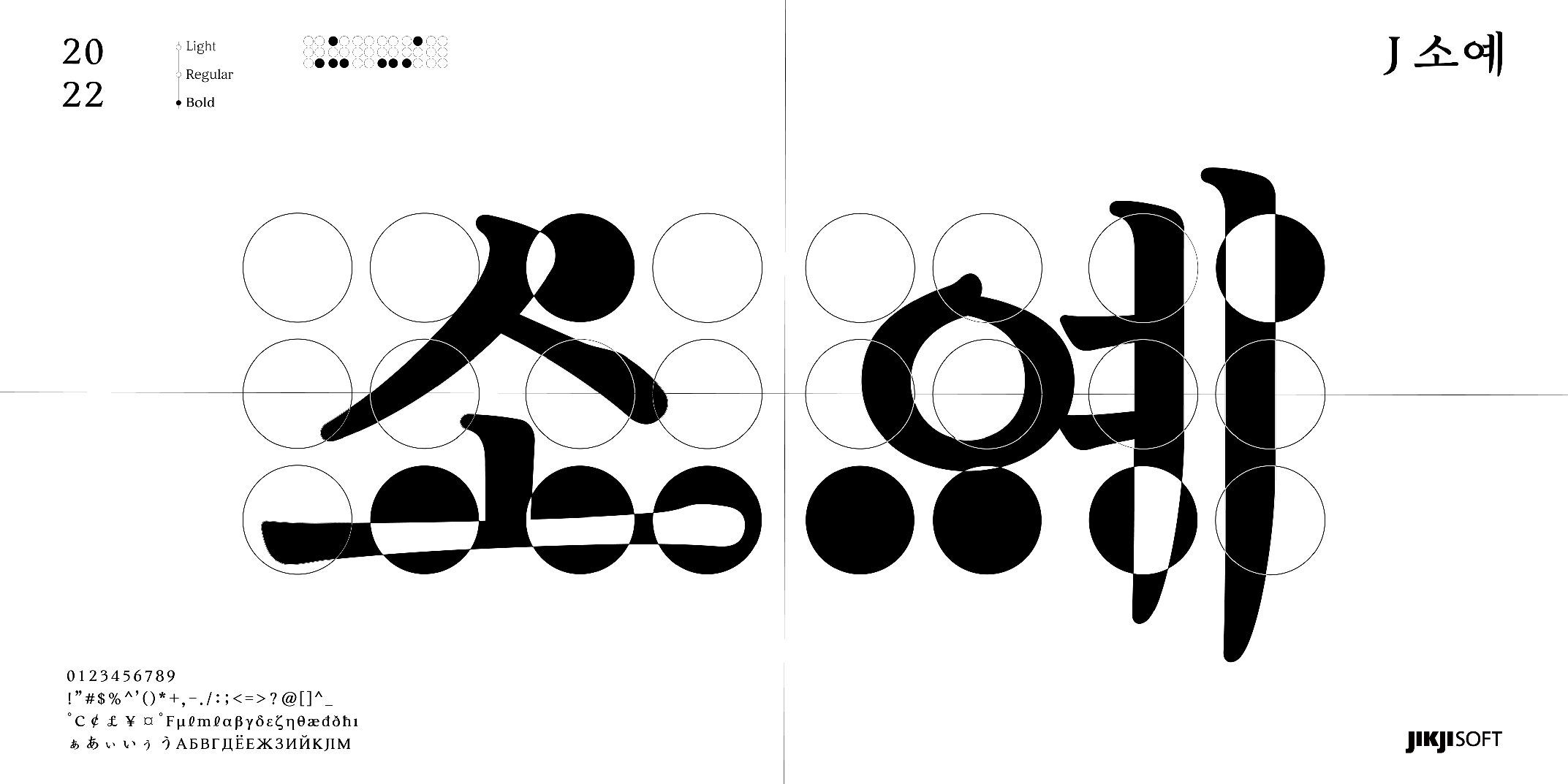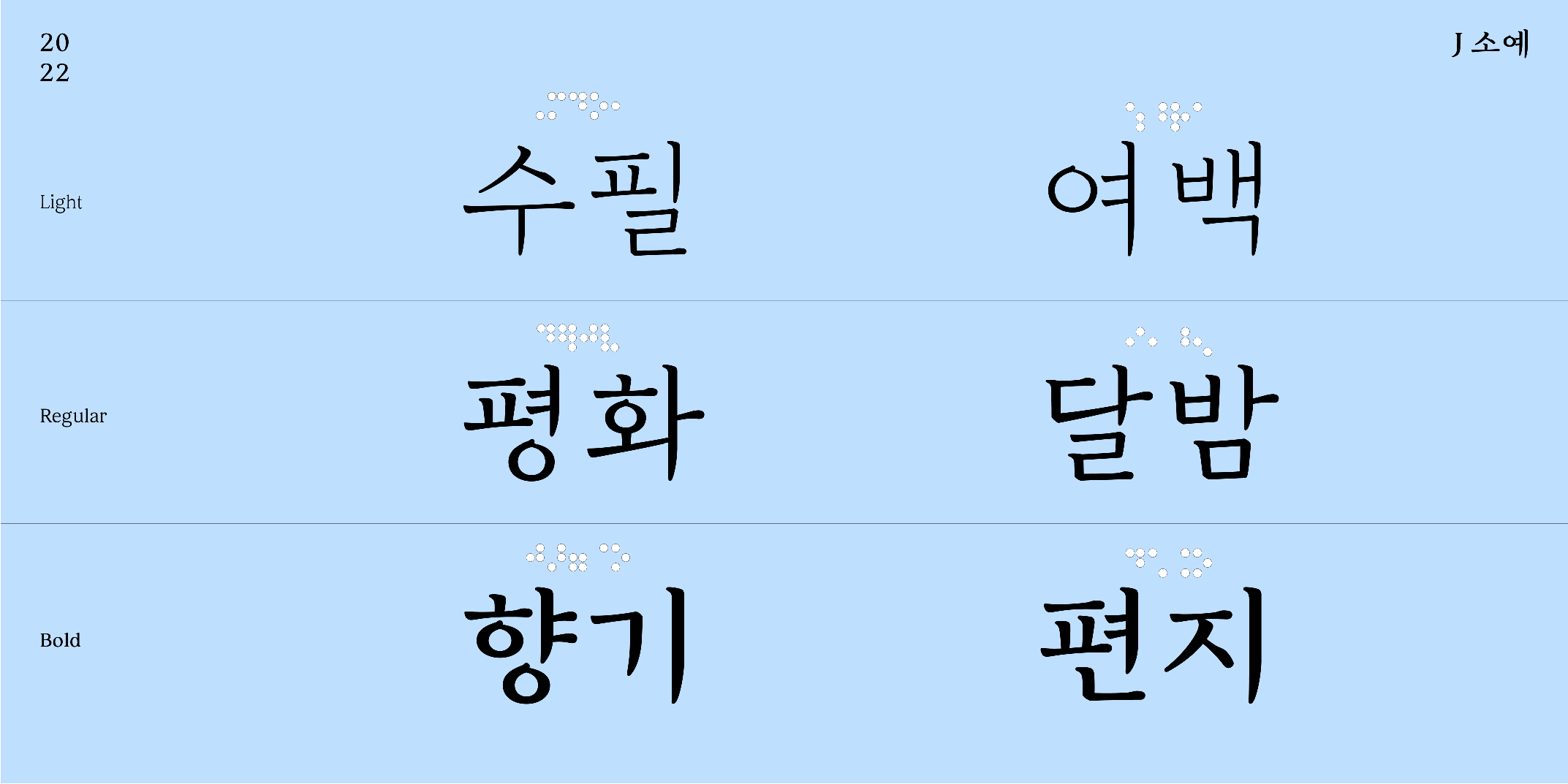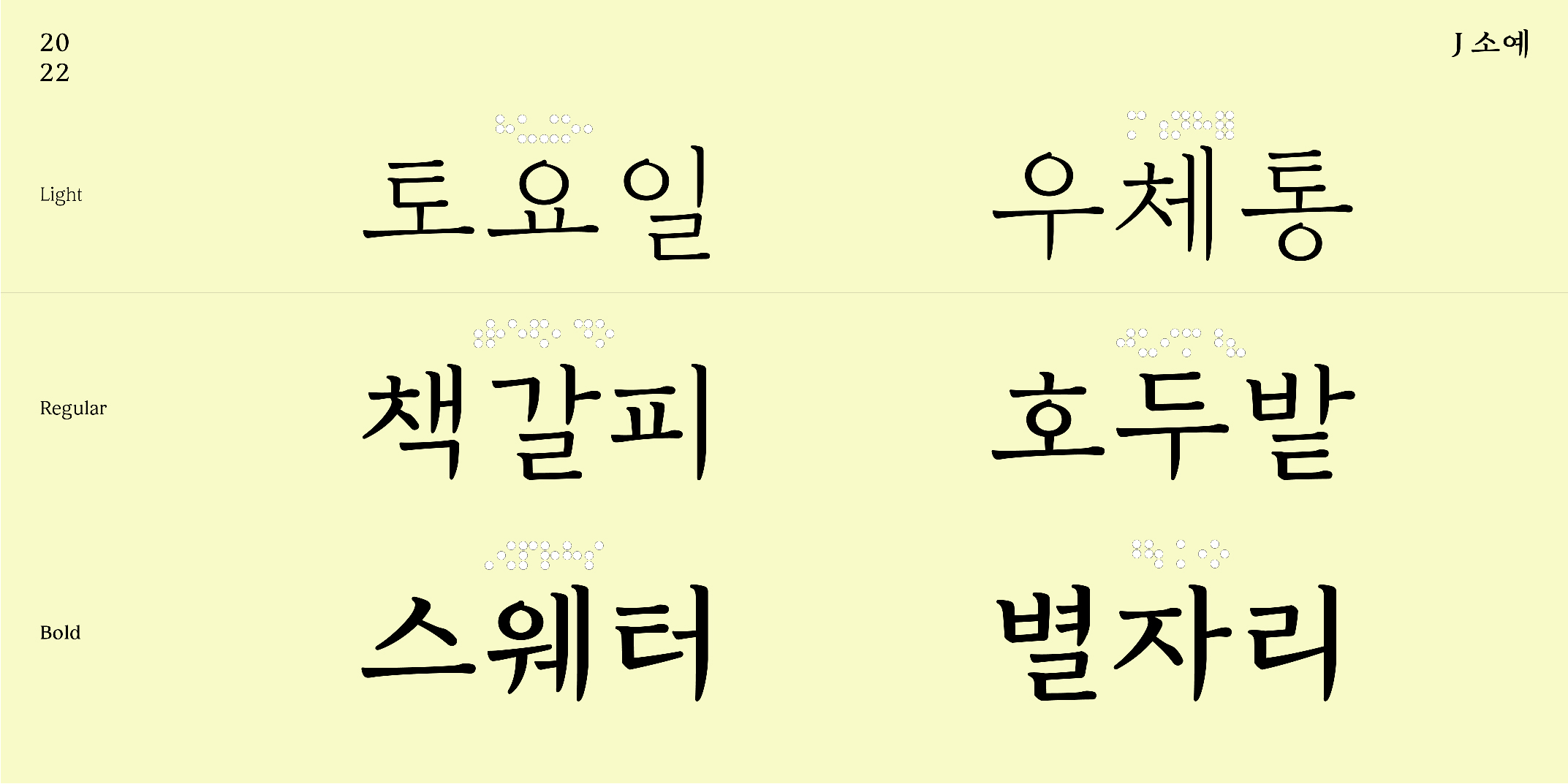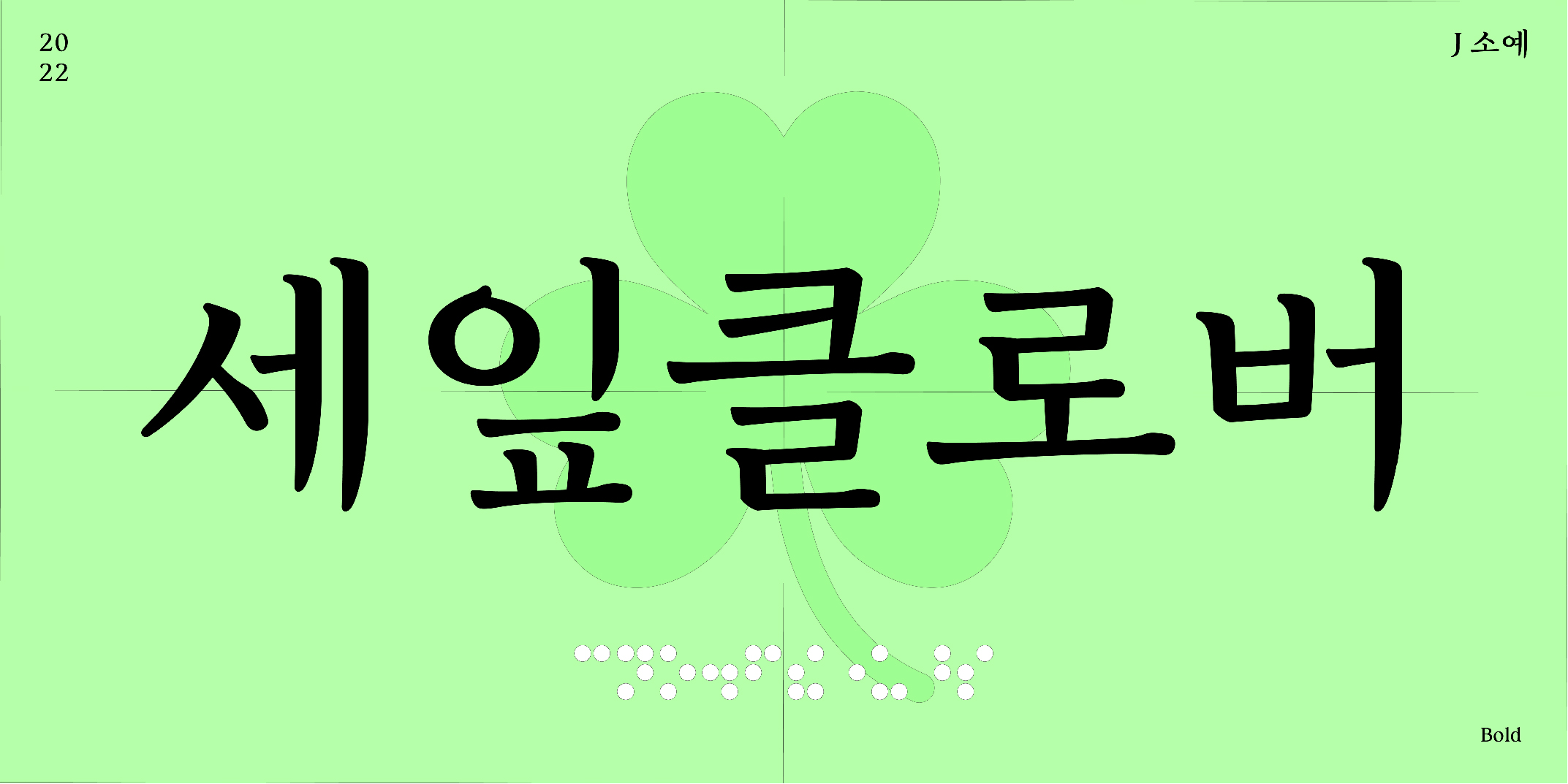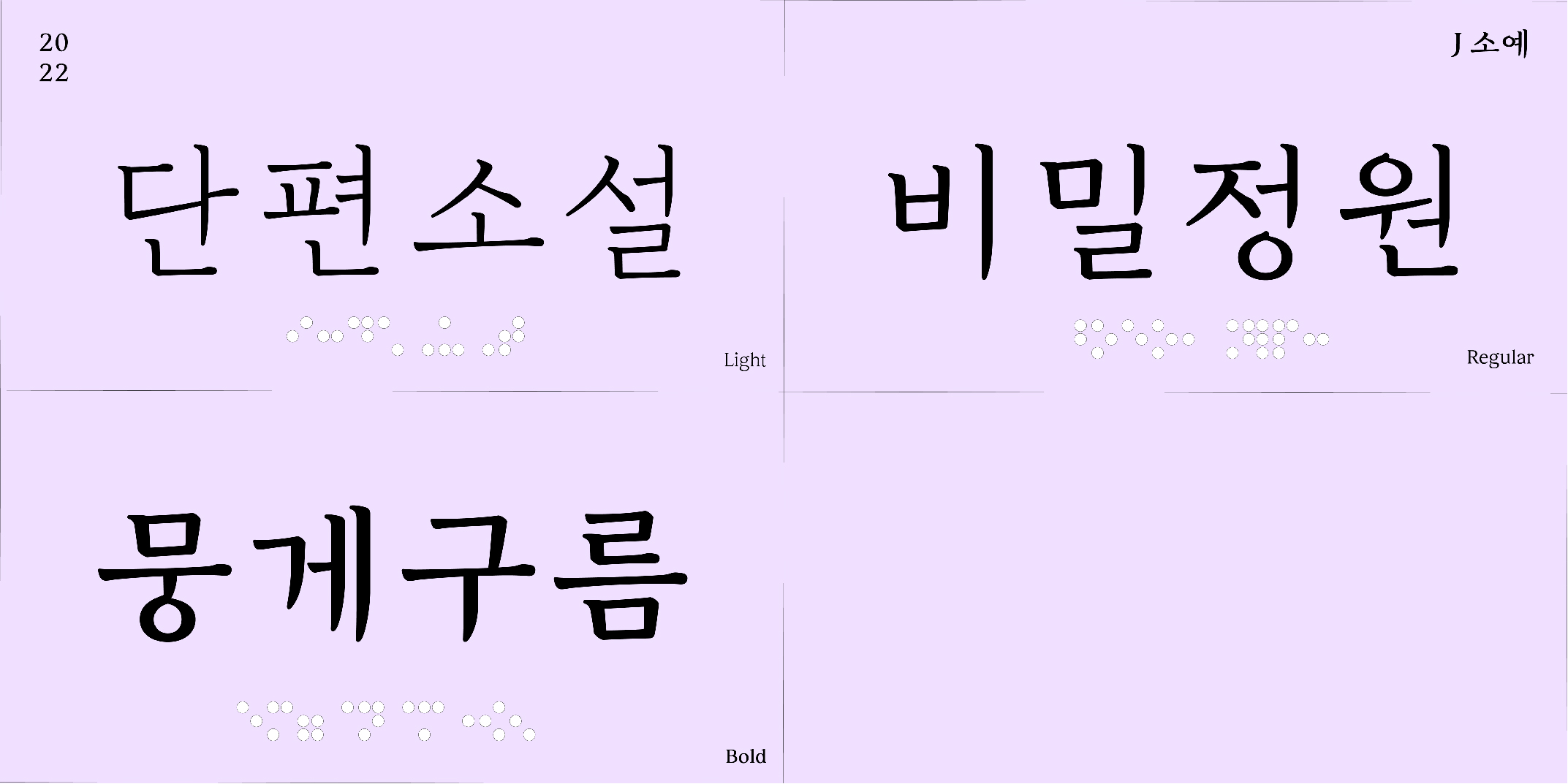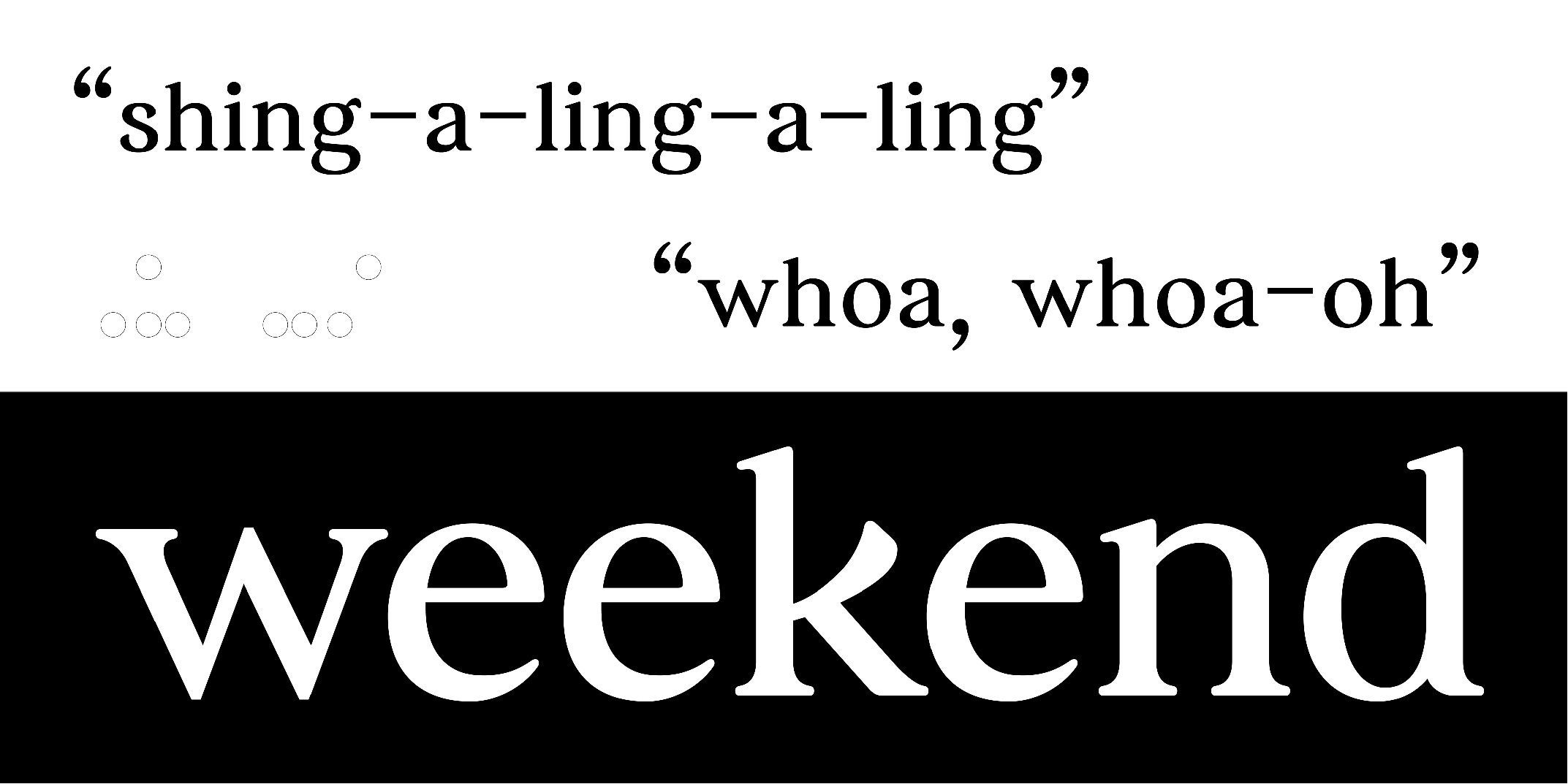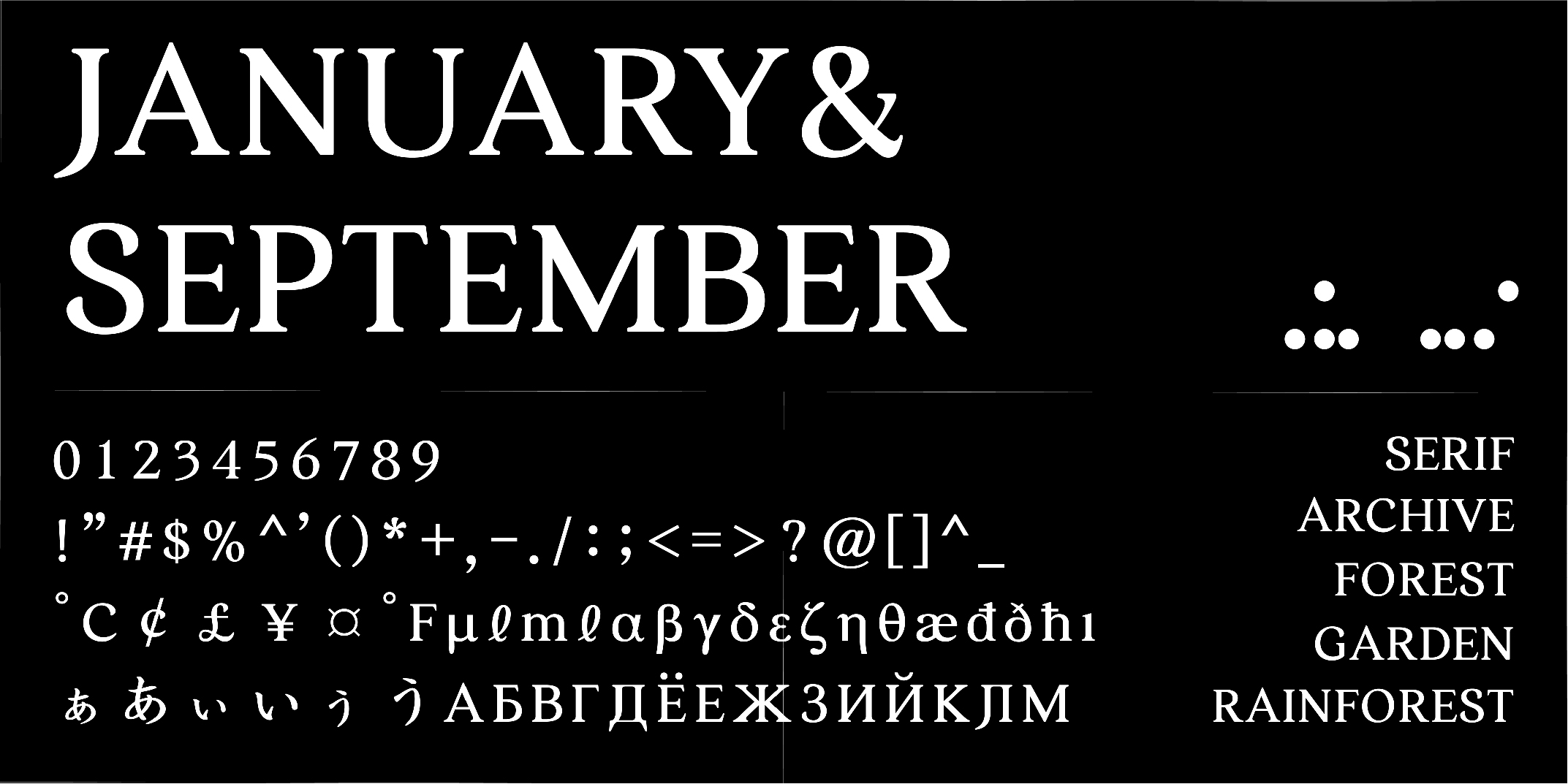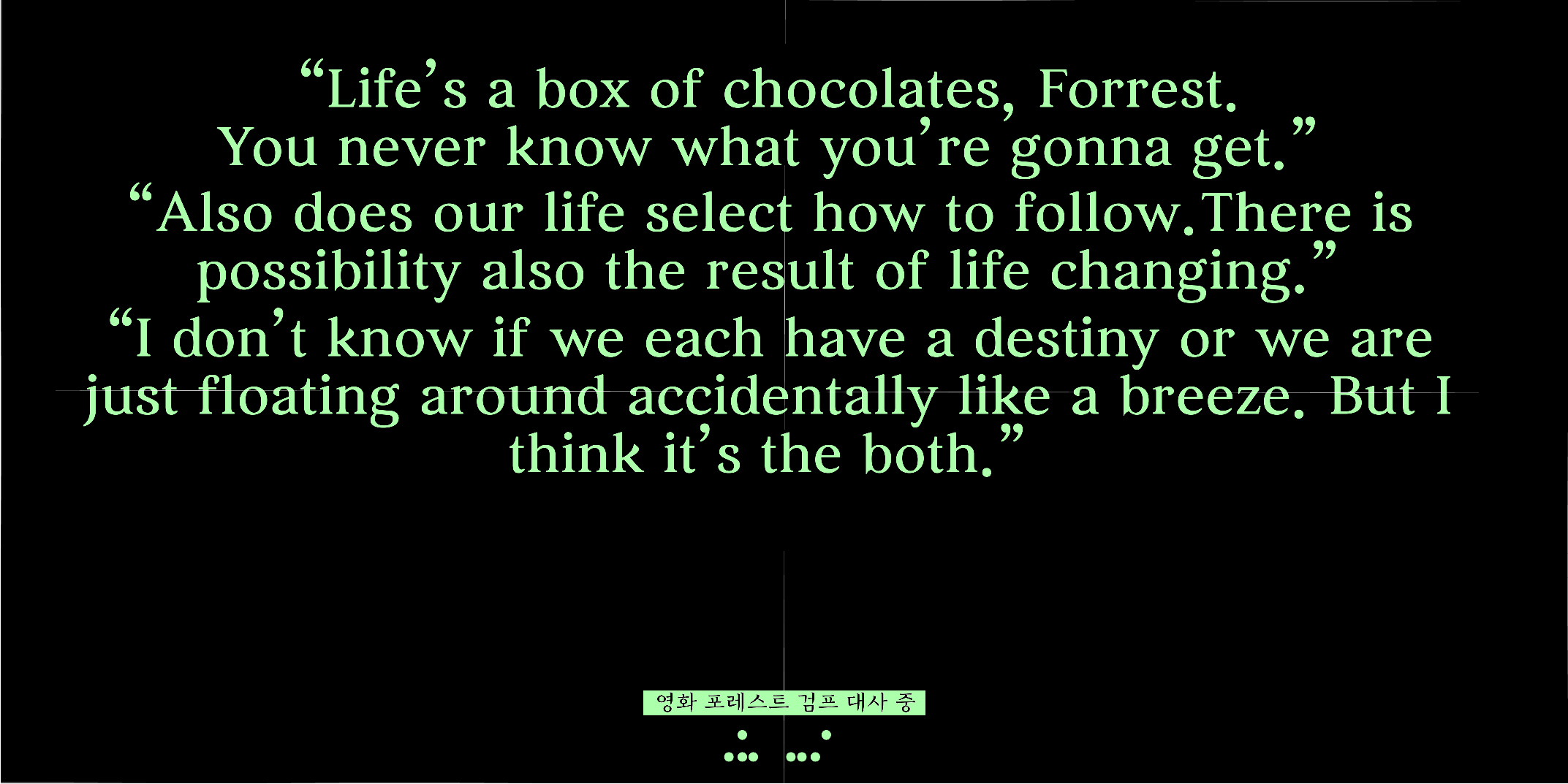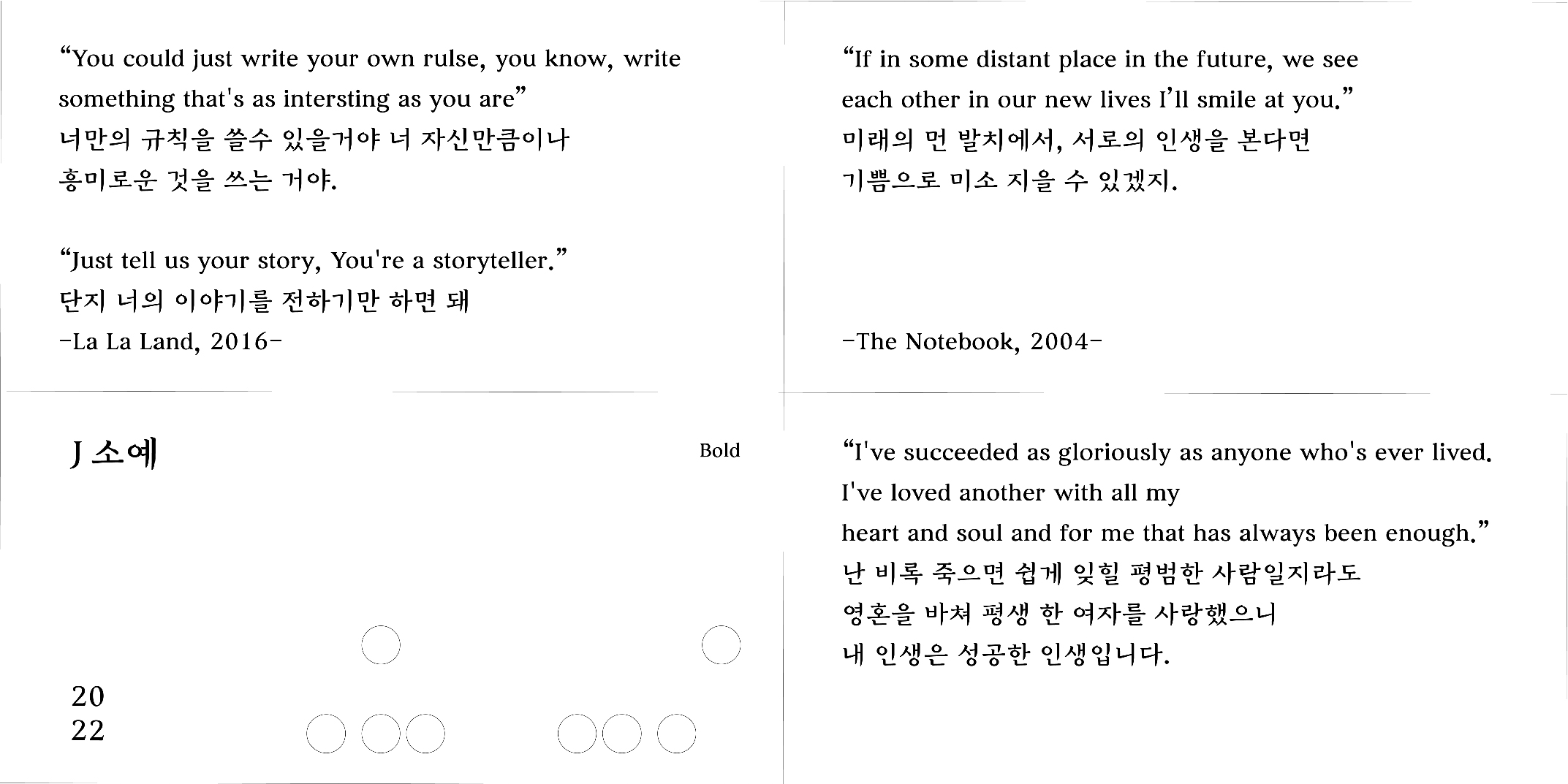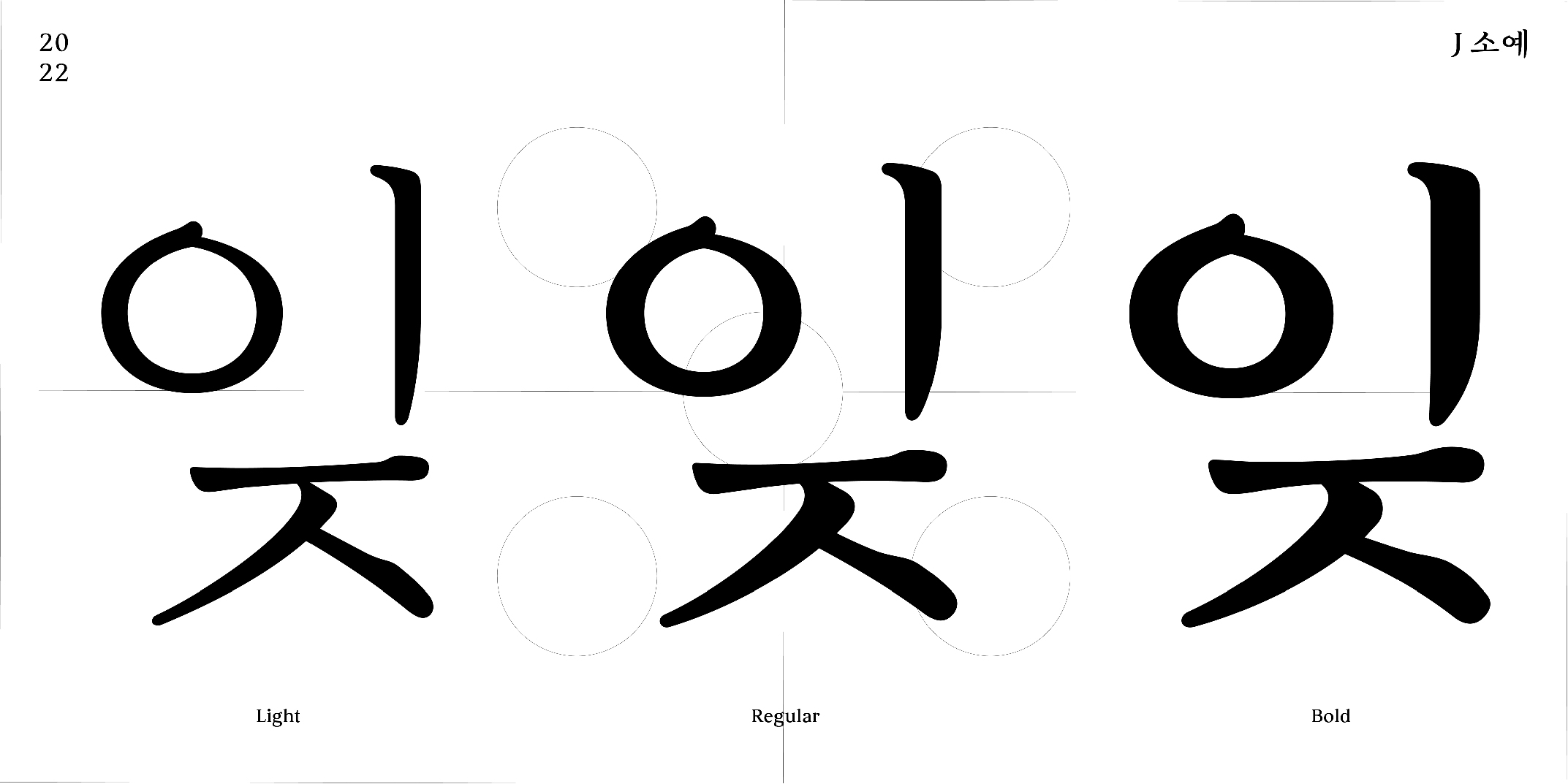
직지소프트에서 오랜 시간 동안 다듬어온 2022년 신서체 <J소예> 를 소개합니다.
직지폰트의 대표주자 SM명조체를 이을 손글씨 명조체 J소예가 출시되었습니다.
특별한 스토리를 다음 서체인 만큼 서체와 기획부터 형태까지 온전히 느낄수 있도록
서체 전용 사이트도 개발되었습니다.
단아하고 정성이 담긴 손글씨 명조체를 만나보세요.
글자기획 | 정성이 담긴 소담한 손글씨
J소예는 박두성의 <훈맹정음>으로부터 시작되었습니다.
박두성은 시각장애인의 세종대왕이라고 불리는 분으로 맹인을 위한 한글 점자를 창시하였으며 한국 시각장애인의 교육자이십니다.
우연히 접한 <훈맹정음> 자료에서 맹인을 위해 만든 한글 점자와 함께 한 글자 한 글자 정성스럽게 쓴 손글 씨는 J소예의 구조적 틀과 자소 디자인에 많은 영감을 주었습니다.
한글이 여러 자모가 모여 하나의 글자가 되는 모아쓰기 방식으로 이루어지는 것과 마찬가지로 한글 점자 또한 동일한 방식으로 구현하고 있습니다.
6개의 원이 하나의 세트가 되는 6점식 점자를 기본으로 초성, 중성 그리고 종성을 구분하여 표현하고 있습니다.
이러한 표현방식은 현재 구현된 사이트의 전체 컨셉의 기본이 되었습니다.
J소예는 한글의 본질에 충실하고자 소담스럽고 예쁜 이라는 순우리말을 서체 이름으로 정했습니다.
한글디자인 | 기존 SM 명조와 비교
명조맛집 직지 소프트에서 야심차게 출시되는 명조체인만큼 기존 SM명조와의 차이점을 궁금해 하실 것 같아 준비했습니다.
위 이미지와 같이 부리와 맺음들이 상대적으로 부드럽지만 디테일은 살린 섬세한 획의 구성이 특징입니다.
한글디자인 | 글자의 특징
가로(ㅡ)와 세로획(ㅣ)의 부리와 맺음 처리, 그리고 ㄱ,ㅍ,ㅌ의 차분한 획의 처리는 느린 획으로 꾹꾹 눌러 쓴 손글씨의 특징을 잘 보여줍니다.
ㅇ과 ㅎ에서의 빼꼼하게 나와있는 꼭지는 이 글자의 개성을 부여합니다.
글자를 자세히 들여다보았을 때는 획의 꺾임 표현과 부드러운 부리와 맺음 처리 는 현대적 감성을 가져가고자 했습니다.
*한 글자 한 글자 확대하여 J소예의 디테일을 확인해보세요.
한글디자인 | 글자의 인상
J소예는 담담하며 고요하고, 단아하며 정갈한 인상의 서정적인 감성을 나타내는 서체입니다.
소담스러운 자소 디자인, 글자의 여백을 최대한 살리면서 자음과 모음의 균형에 초점을 맞추어 고전적이면서도 현대적인 미를 살리려 했습니다.
한글디자인 | 글자의 구성
J소예 Light, Regular, Bold 총 3종으로 구성되어 있으며, 각 굵기별 획 각도 조절과 자소의 일부 디자인의 디테일을 차별화 두어 디자인했습니다.
이는 같은 패밀리 구성 안의 폰트이지만 굵기별로 각기 다른 인상을 줍니다.
라틴 디자인 | 펜글씨와 붓글씨의 조화
펜 글씨를 바탕으로 하는 라틴 알파벳의 감성을 유지하면서도 한글의 붓글씨 필력을 살려 국문과의 균형을 최대한 맞추었습니다.
손글씨의 영향으로 잉크가 맺혀있는 볼륨있는 곡선 을 소문자 k, f, g, c, r, s 에서 나타내었습니다. 볼륨 있는 곡선의 느낌으로 조화로운 인상을 표현했습니다.
문장부호는 국문과 영문의 획,굵기, 자소의 형태를 반영하여 일관되며 자연스럽게 어울리도록 제작하였습니다.